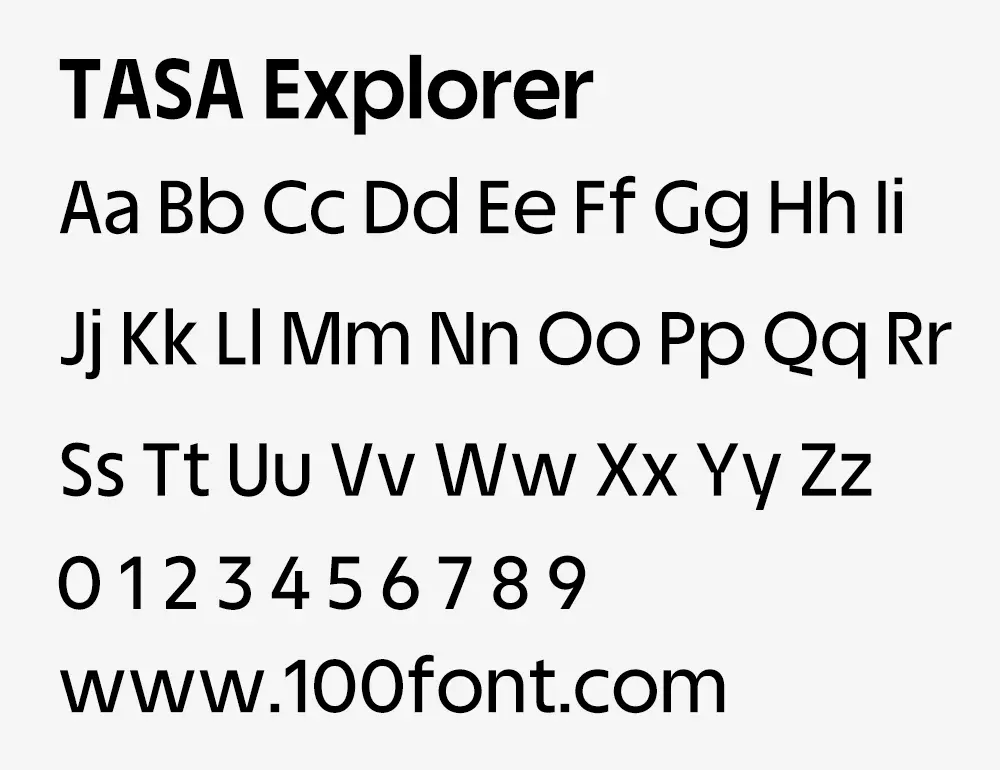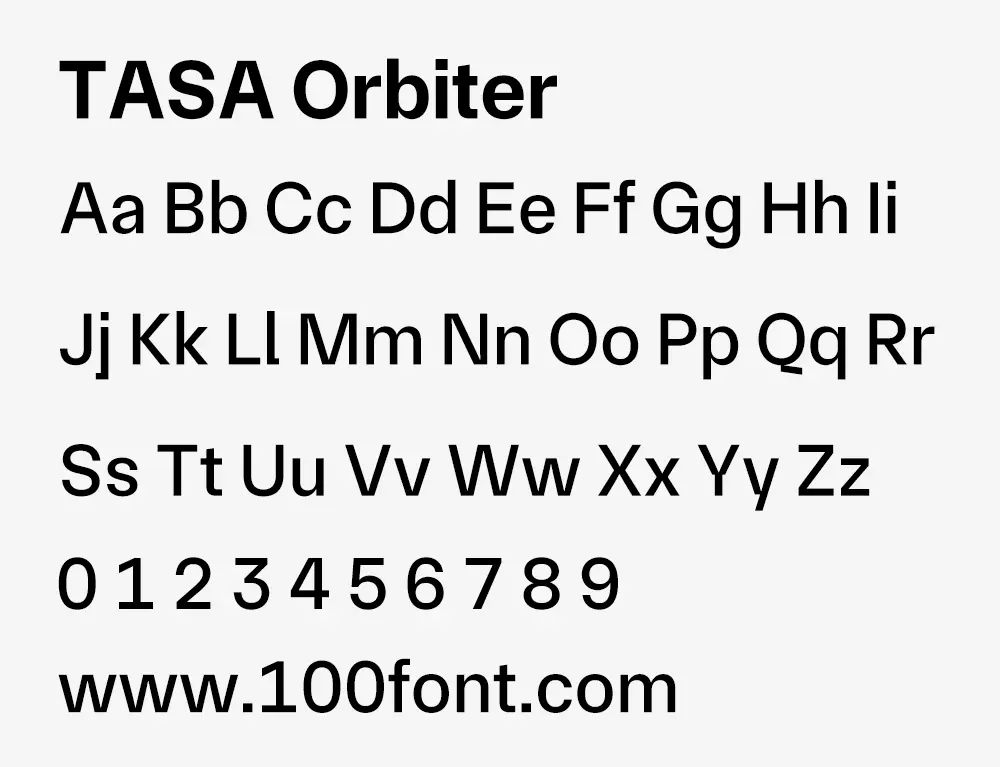
TASA預覽
TASA介紹
TASA字體系列由TASA Explorer和TASA Orbiterl兩套字體組成,這兩種定製字體專為臺灣航天局品牌重塑而設計。TASA Explorer 是一款具有大膽創新外觀的展示字體,適用於標題、標誌;而 TASA Orbiter 是一款多用途無襯線字體,適用於正文文本、副標題,具有良好的可讀性和適應性。